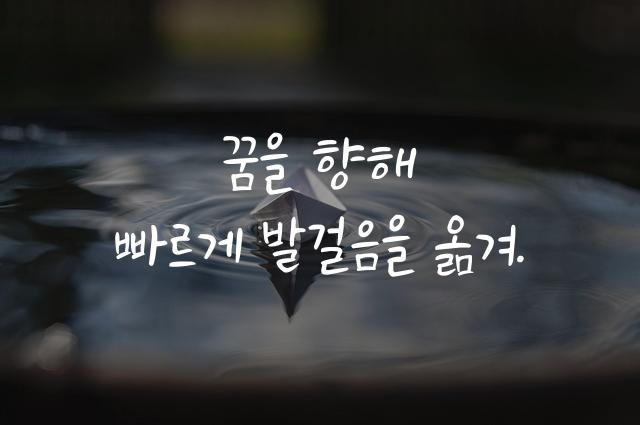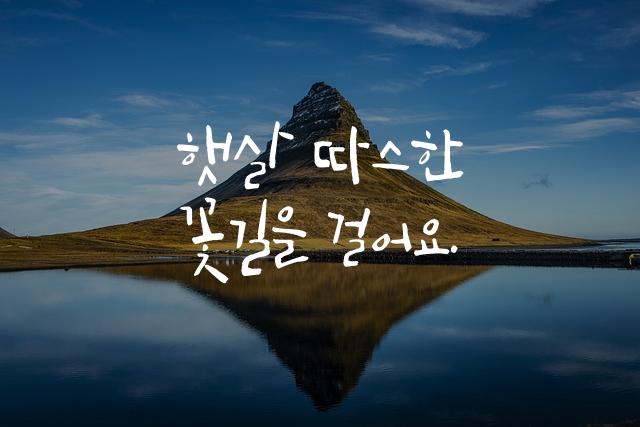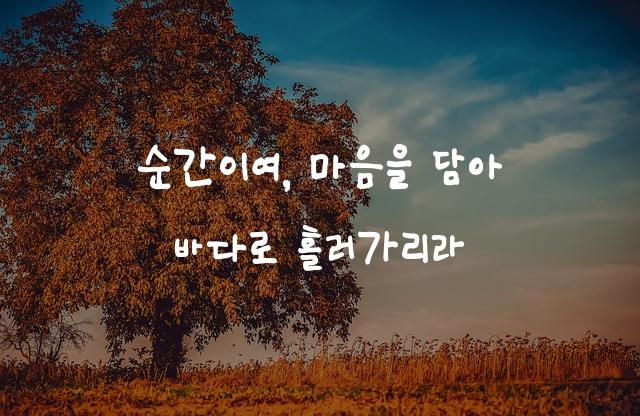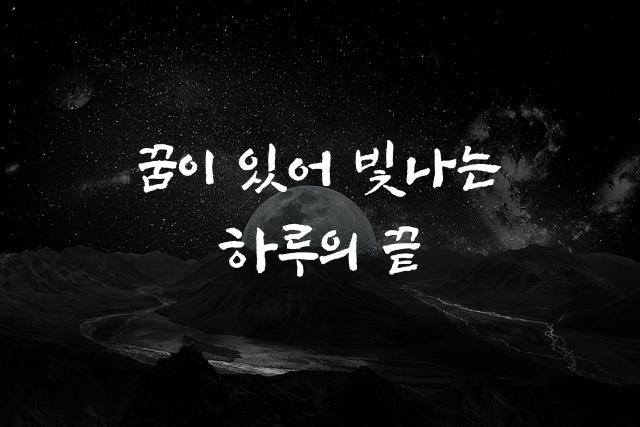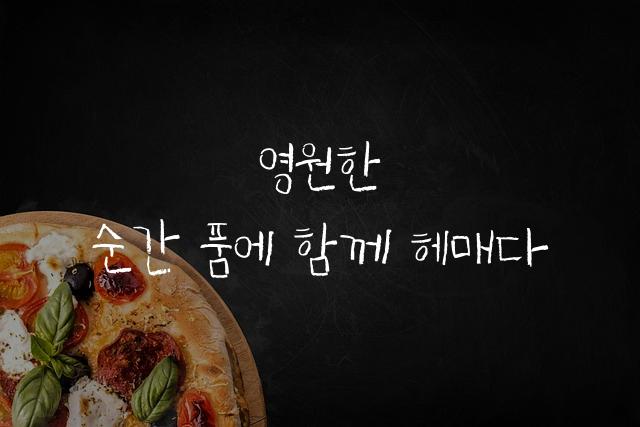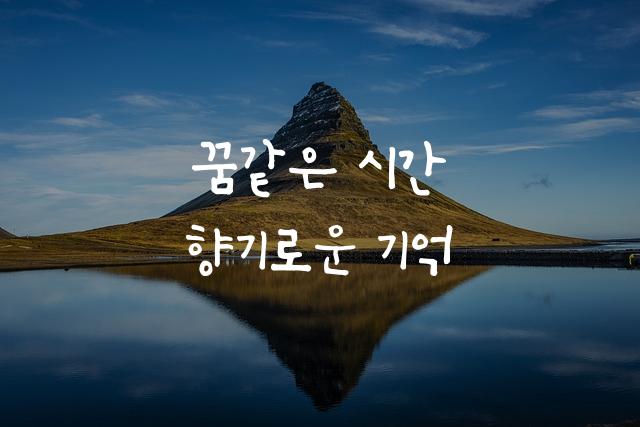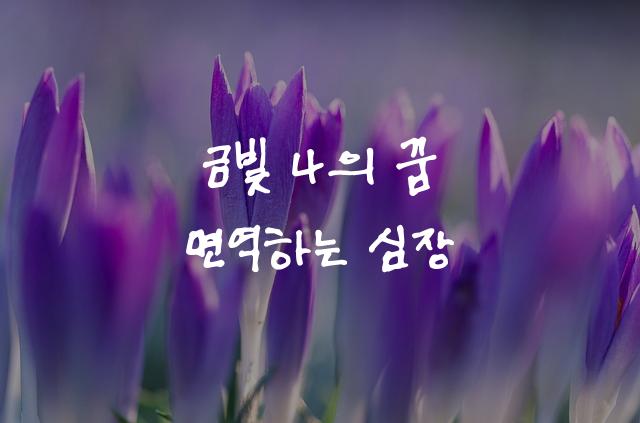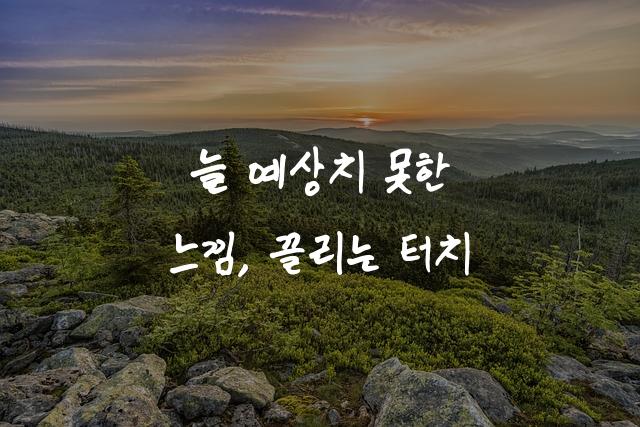
‘신과장’은 상상토끼에서 제작한 캘리그라피 스타일의 폰트로, 어른 손글씨의 자연스러운 흐름과 세련된 느낌을 강조합니다. 이 폰트는 감성적인 느낌을 전달하며, 디지털과 아날로그의 경계를 자연스럽게 연결해 줍니다.
손글씨, 펜/붓터치, 감성적인, 부드러움 계열의 생김새를 가지고 있으며
로고 디자인, 브랜딩, 광고 문구 등에서 자주 활용되며, 효과적인 메시지 전달에 적합합니다.
이 폰트는 광고/마케팅, 크리에이티브, 금융/비즈니스 분야에 잘 어울리며,
현대적, 세련된, 전문적인 느낌을 담고 있는 것이 특징입니다.